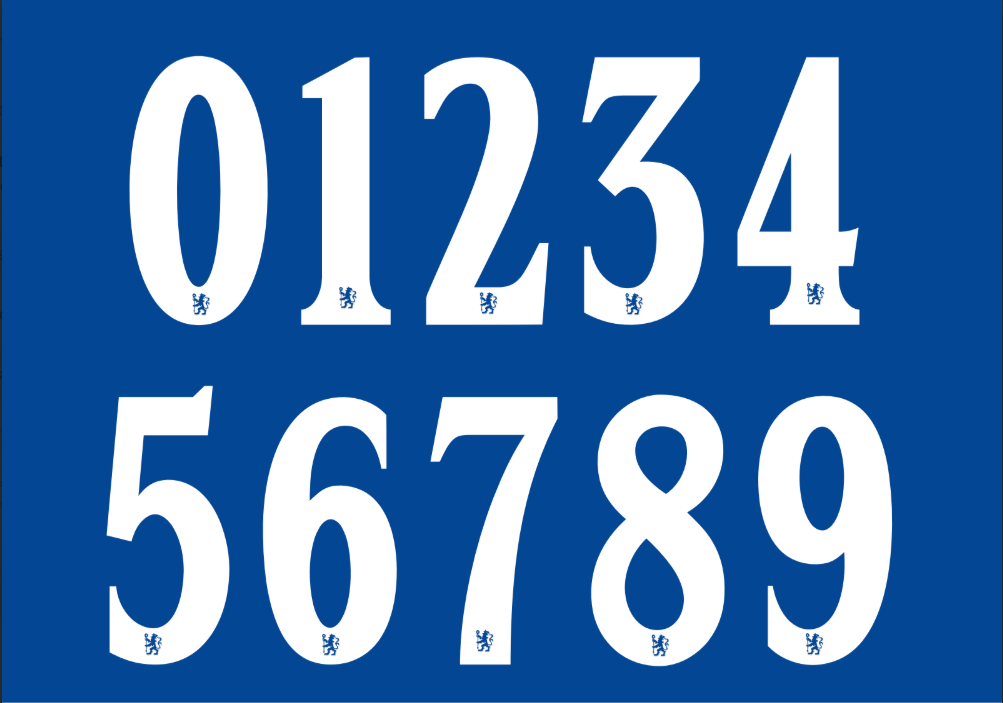
A hegemonia azul em Londres se renova a cada temporada. Para a jornada 2025/2026, a Nike preparou para o Chelsea FC uma identidade visual que reflete a modernidade e a ambição do clube em Stamford Bridge.
- Conteúdo: Alfabeto completo (caixa alta) e numeração oficial com o logo do clube na base (versão vetorizada opcional).
Estilo Visual e Design
A tipografia desta temporada segue o padrão inovador da Nike, apostando em uma estética limpa, mas agressiva. Diferente de anos anteriores, a fonte 2025/26 apresenta cortes diagonais mais acentuados nas extremidades dos números, transmitindo uma sensação de velocidade e dinamismo.
Ela foi projetada para ter alto contraste tanto no tradicional uniforme azul (Home Kit) quanto nas variações alternativas (Away e Third Kits), garantindo legibilidade perfeita nas transmissões em 4K. É a escolha obrigatória para reproduzir com fidelidade as camisas de craques que brilham na Inglaterra.
Dica de Uso: Para estampas em camisas escuras, utilize a fonte na cor branca com contorno (stroke) sutil para replicar o efeito oficial de campo.